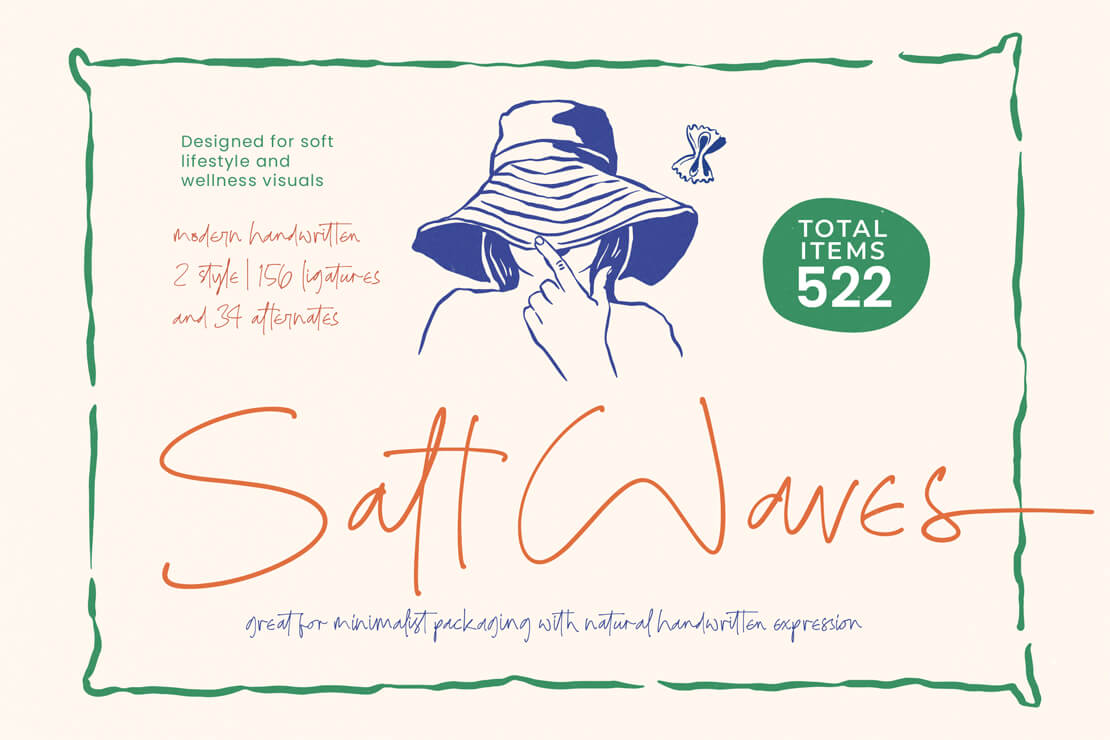
Salt Waves
Eine moderne Handschrift mit entspannter Note. »Salt Waves« von Pricilia Design steht kostenlos zum Herunterladen bereit.
Salt Waves Font
Das Schriftbild zeichnet sich durch einen lockeren und natürlichen Charakter aus. Damit bietet sich der Font für Gestaltungen an, bei denen eine persönliche, handschriftliche Anmutung gefragt ist.
Die Schrift umfasst zwei verschiedene Stile mit insgesamt über 500 Glyphen. Für ein abwechslungsreiches Erscheinungsbild sorgen 150 Ligaturen sowie 34 alternative Buchstabenformen. Zudem ist der Zeichensatz so ausgebaut, dass auch deutsche Umlaute enthalten sind.